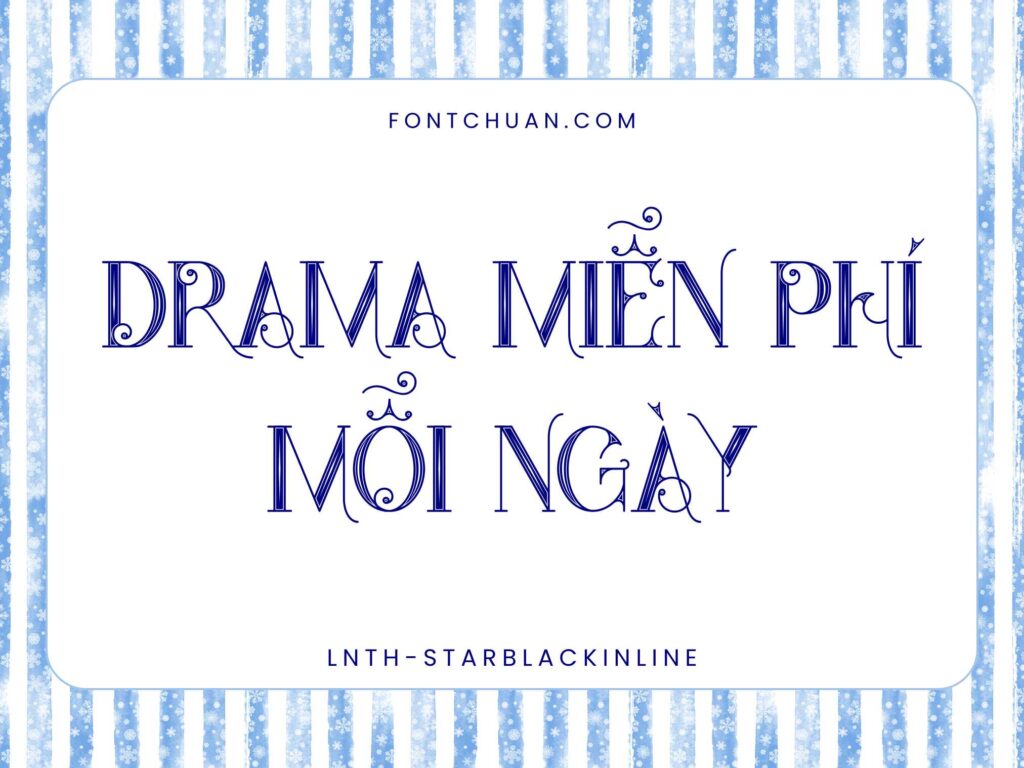
Font LNTH Starblackinline Việt Hóa
Tác giả Font: Peter Olexa
Font StarBlackInline là một font chữ đậm chất nghệ thuật với thiết kế độc đáo, mang phong cách mạnh mẽ và nổi bật. Với các đường nét in đậm kết hợp với hiệu ứng inline bên trong từng ký tự, font này tạo ra hiệu ứng ấn tượng, phù hợp cho các thiết kế poster, tiêu đề lớn hoặc các dự án mang tính thương hiệu mạnh. StarBlackInline mang đến cảm giác hiện đại, sáng tạo và có chút hoài cổ, giúp nâng tầm thiết kế đồ họa của bạn
Phiên bản này đã được Việt hóa bởi LNTH, hỗ trợ đầy đủ tiếng Việt cùng hơn 50 ngôn ngữ khác, giúp người dùng dễ dàng ứng dụng trong thiết kế quốc tế. Font StarBlackInline được các thành viên Font Chuẩn sưu tầm và đăng tải nhằm mang đến một sự lựa chọn đặc biệt cho những ai yêu thích phong cách typography táo bạo và cá tính
Về đặc điểm thiết kế, StarBlackInline có các nét chữ dày dặn với phần inline tinh tế, giúp tăng độ tương phản và chiều sâu. Kiểu chữ này rất phù hợp để sử dụng trong thiết kế tiêu đề, quảng cáo, bao bì sản phẩm, và các thiết kế branding
Font StarBlackInline được ứng dụng rộng rãi trong các sự kiện như lễ hội, chiến dịch quảng bá thương hiệu hoặc các thiết kế sáng tạo. Nó phù hợp với nhiều ngành nghề như quảng cáo, bất động sản, công nghệ, giáo dục